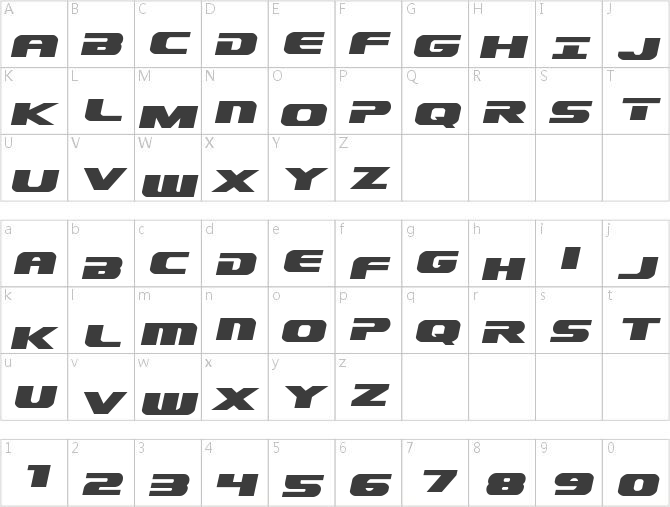
dekarangerexpandital 詳情頁
dekarangerexpandital字體字庫是一款讓人賞心悅目、百看不厭的英文字體,適合各類廣告和產(chǎn)品包裝設(shè)計(jì)應(yīng)用,字體大小0.03MB,格式為ttf字體,上傳用戶是東情,作者/版權(quán)方為未知